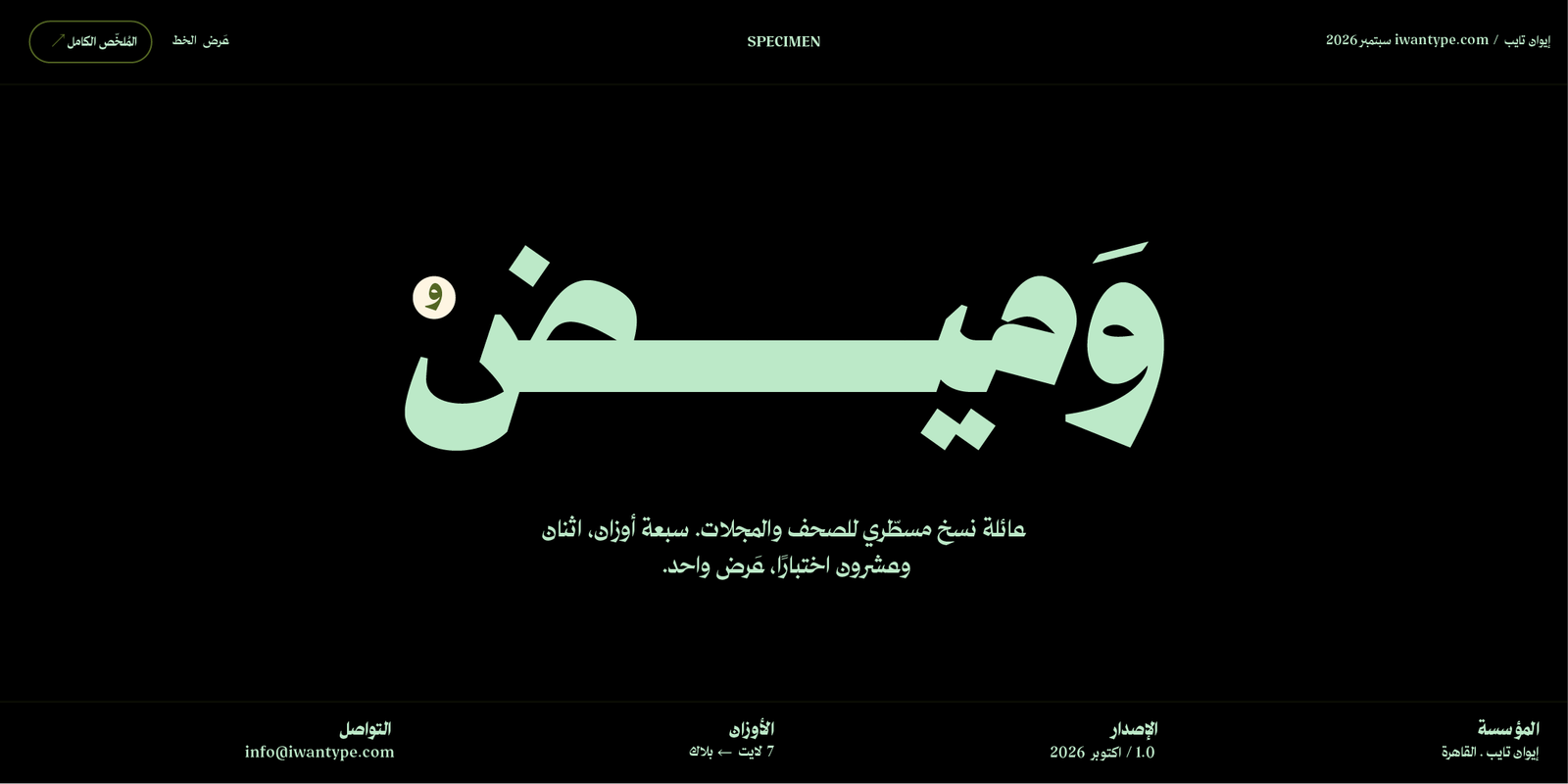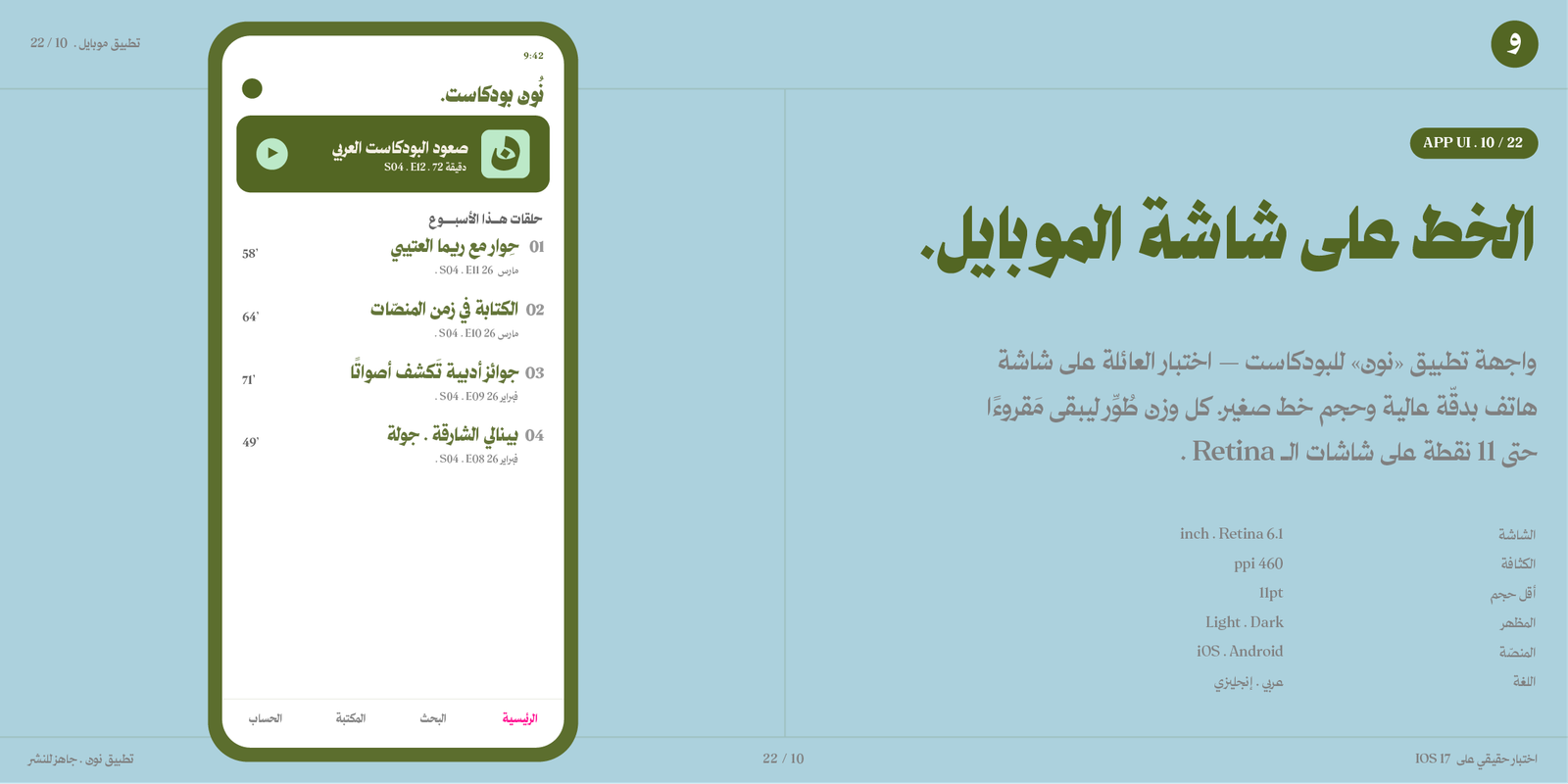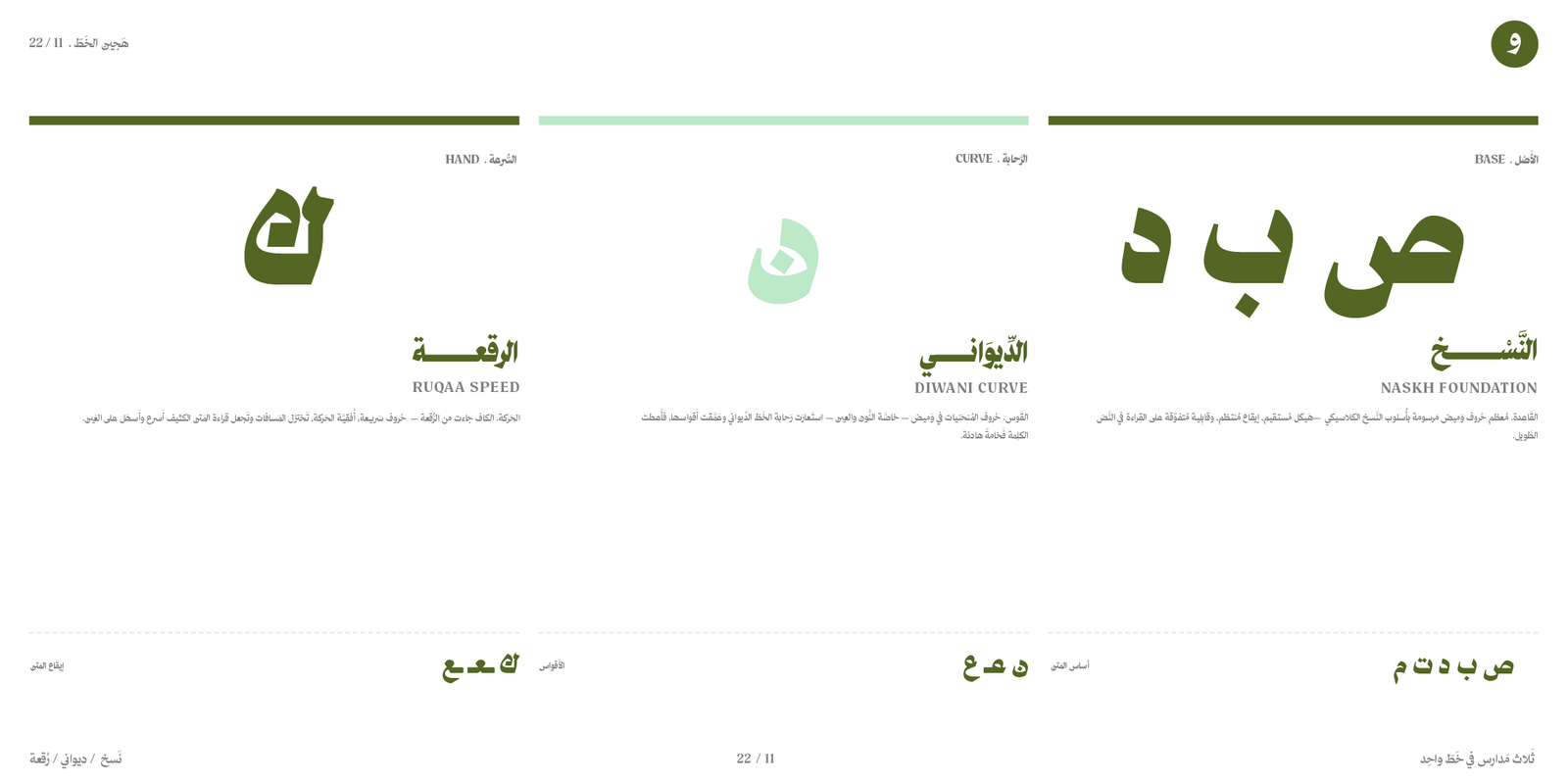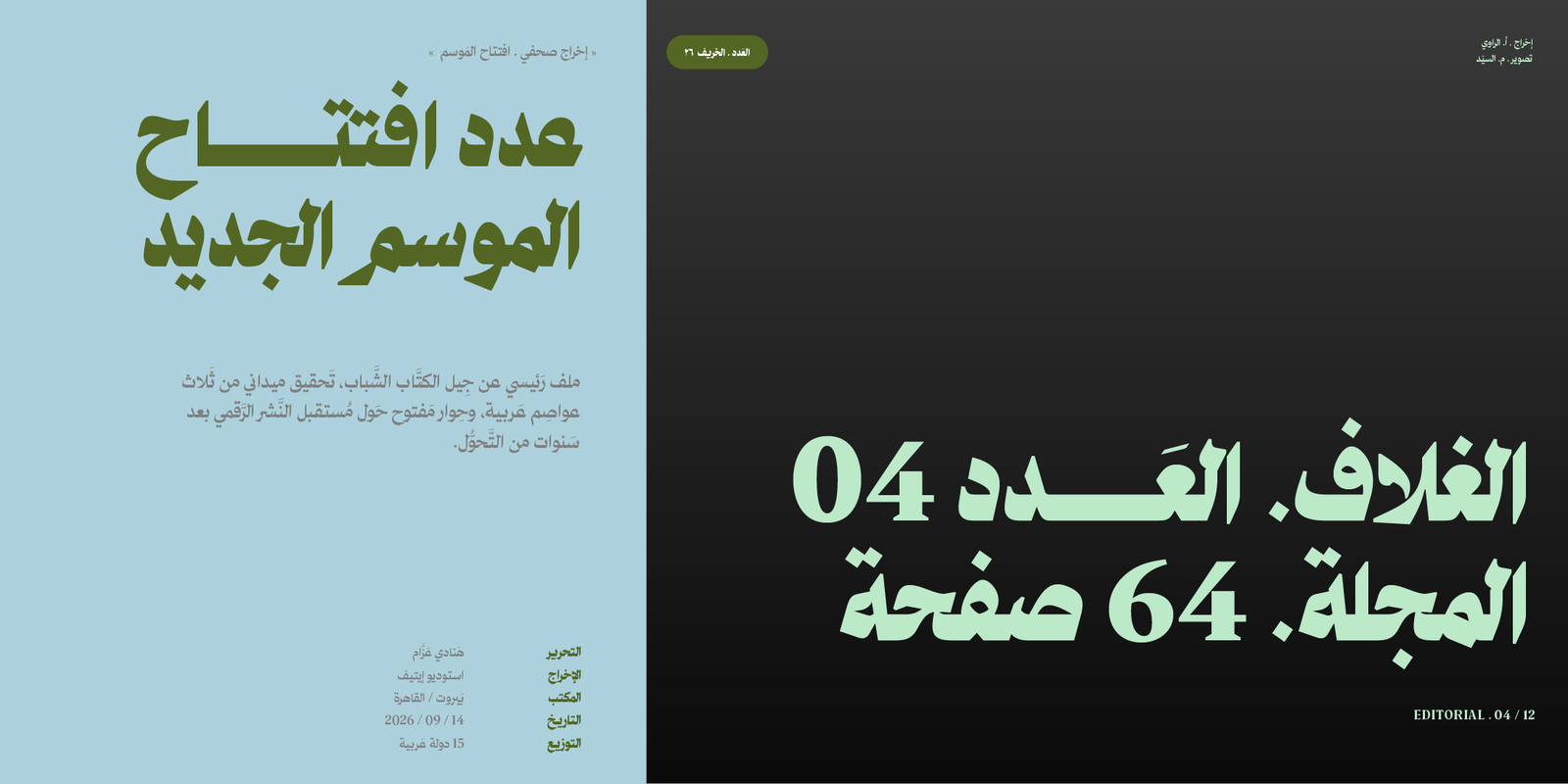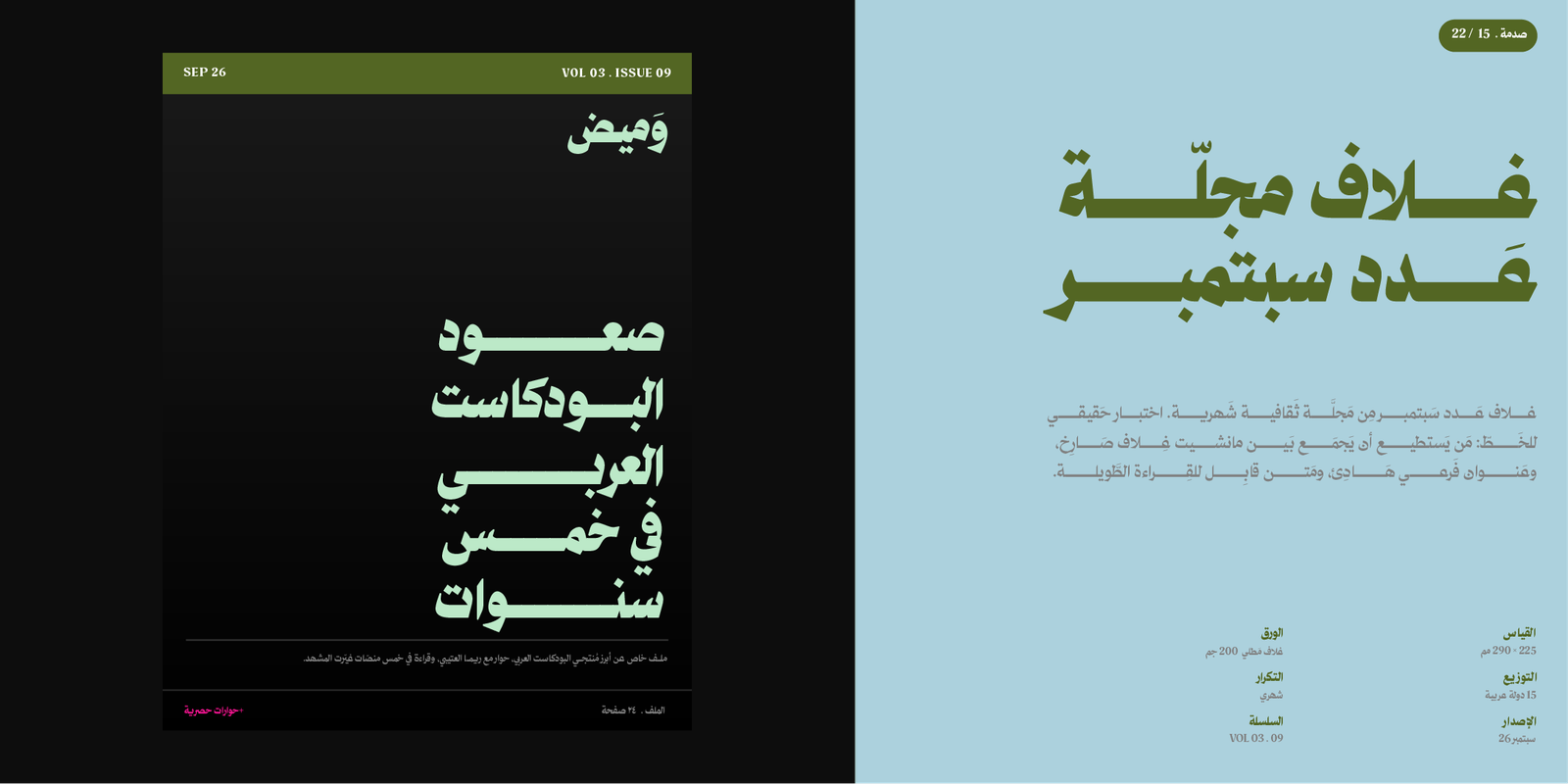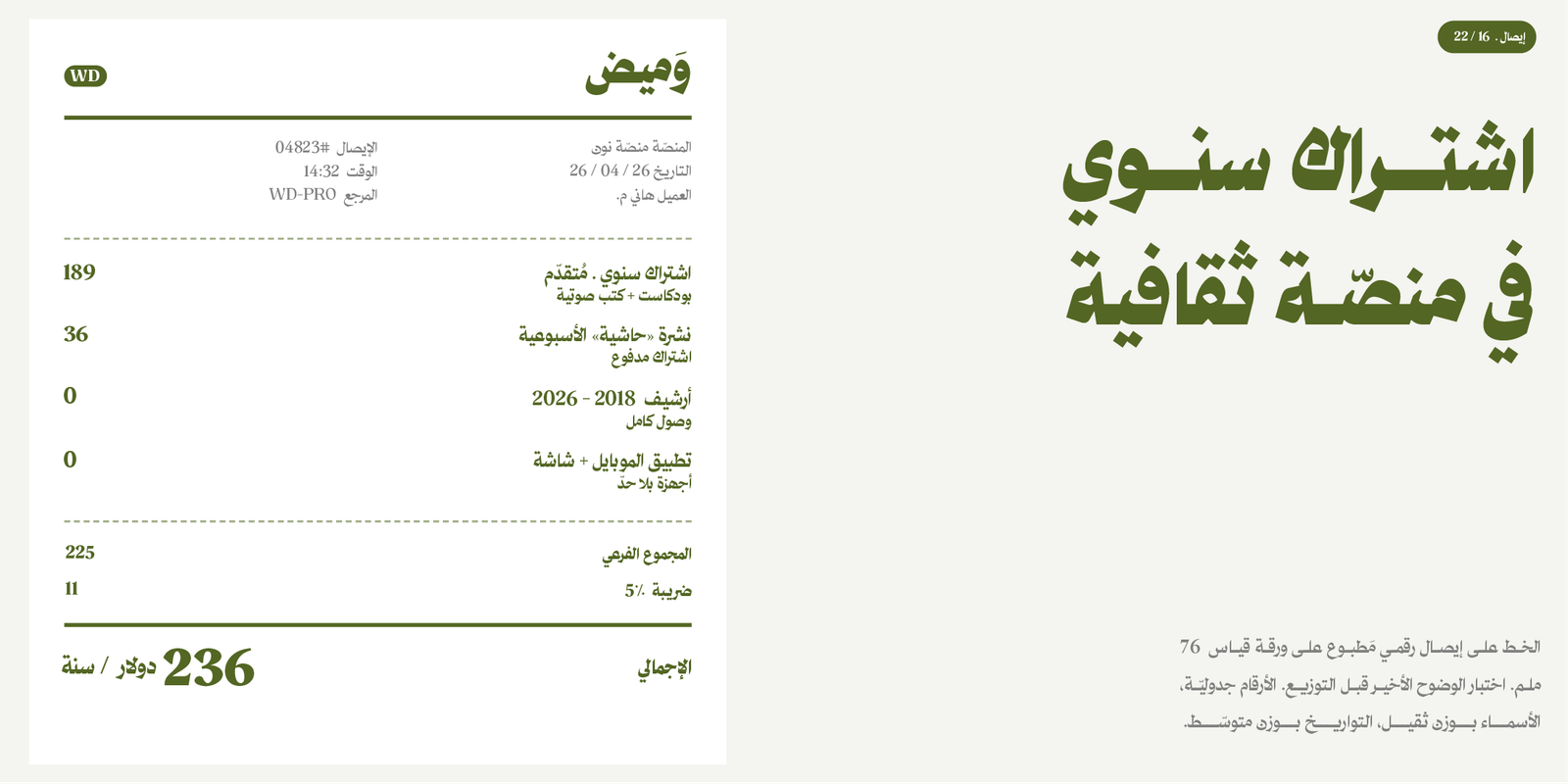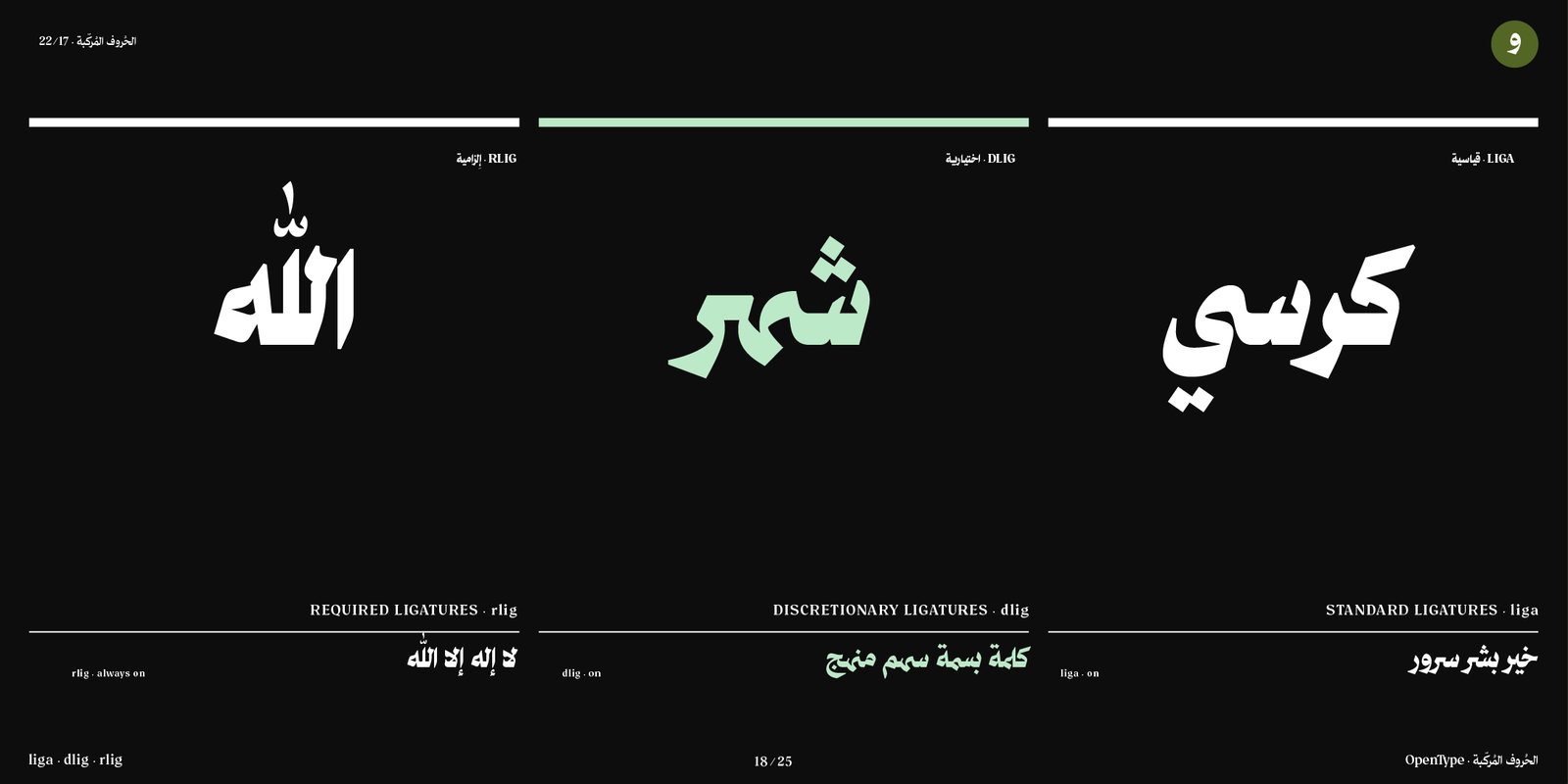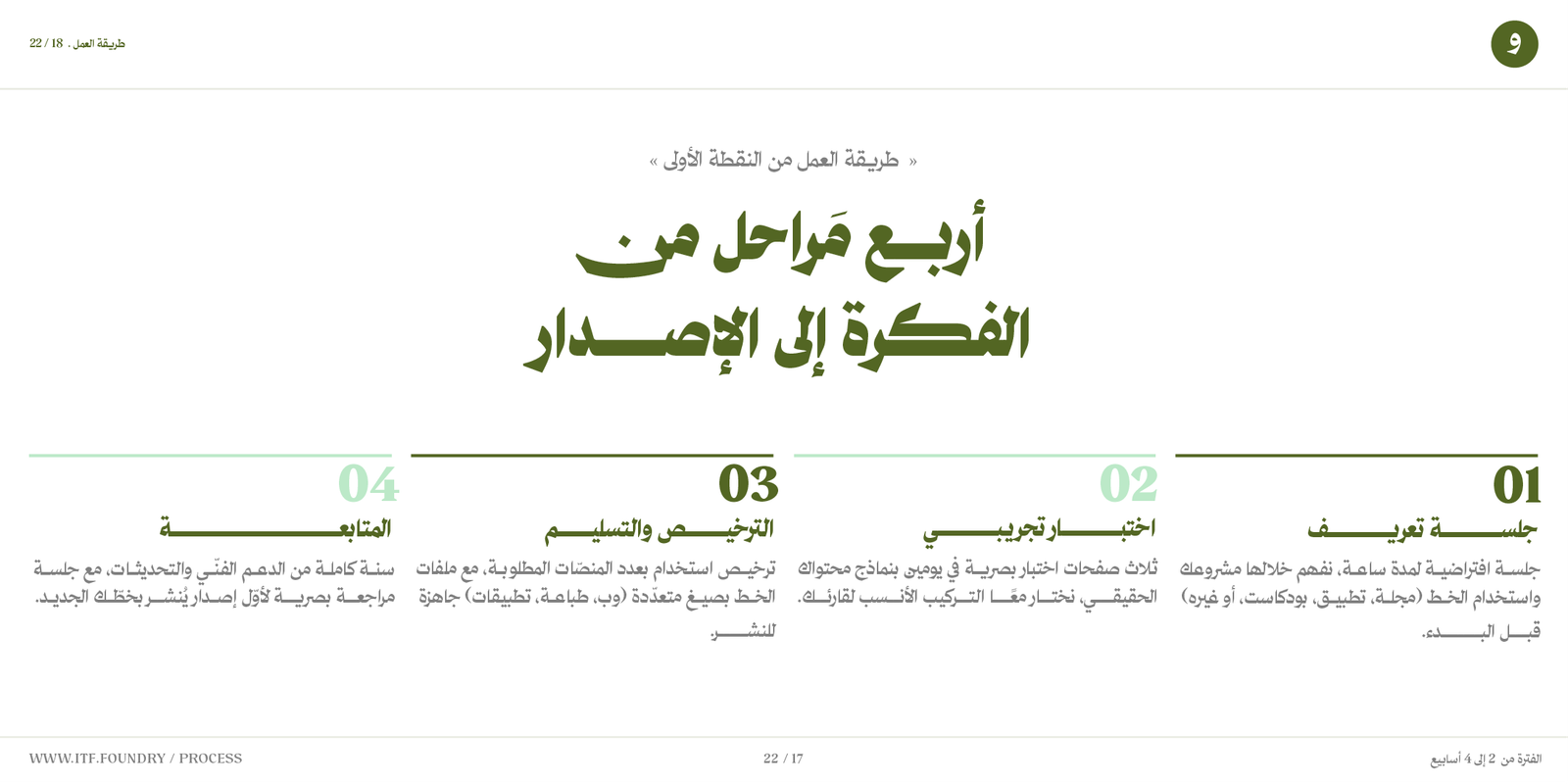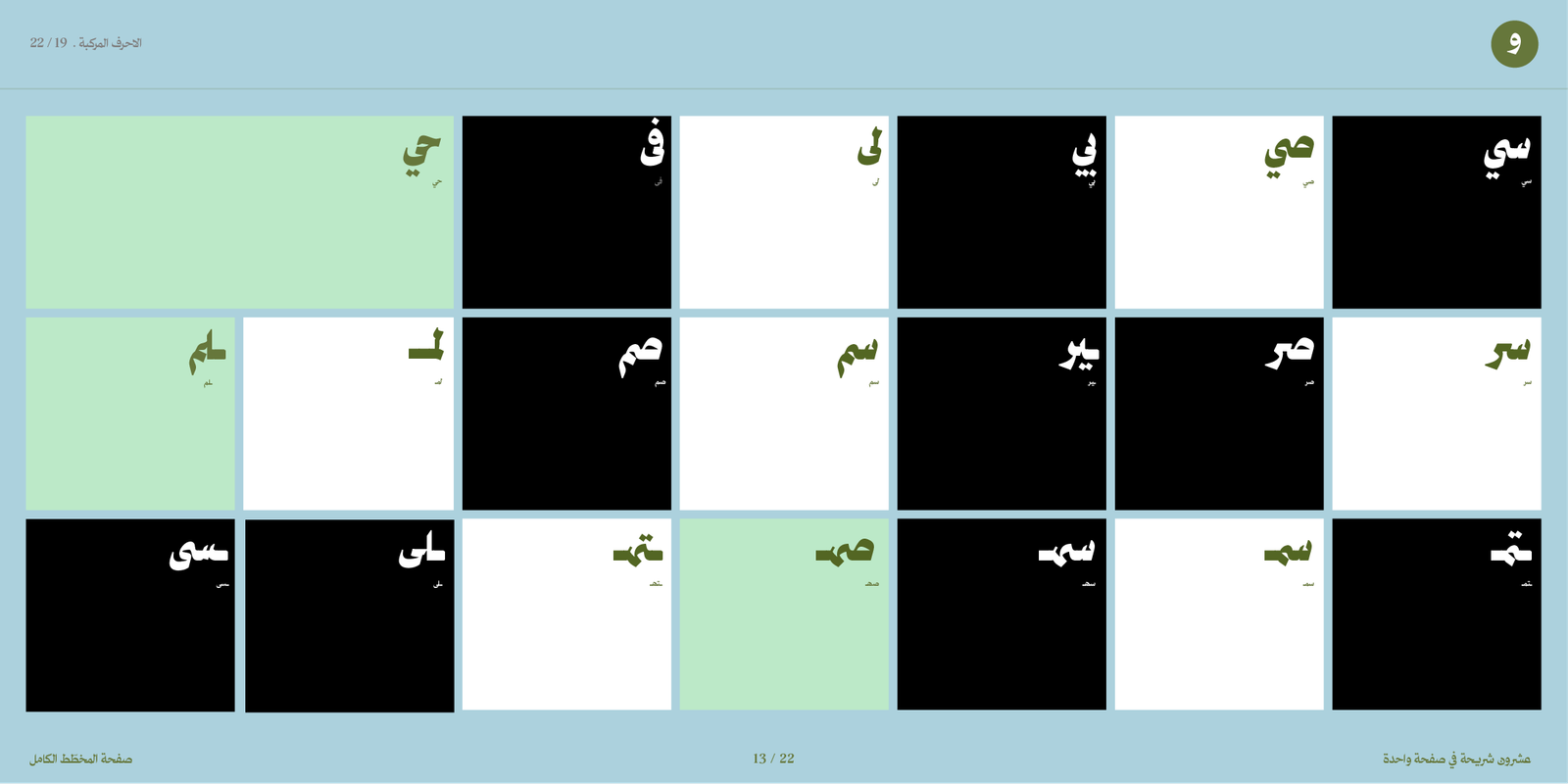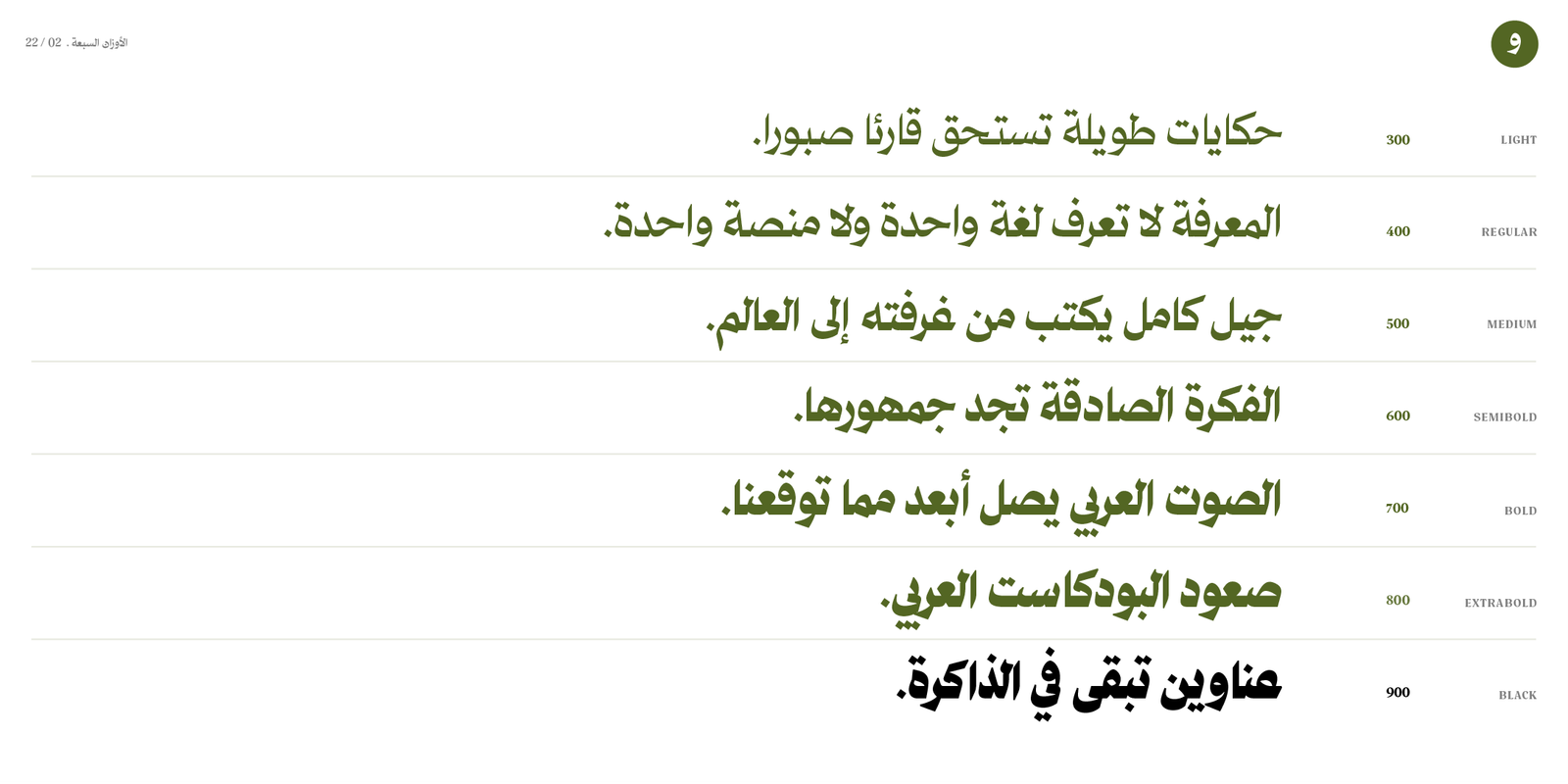
خط وميض – Wameed typeface – خط نسخ حديث للصحف والمجلات
خط «وميض» خط نسخ عربي حديث بُني على أساس النسخ المسطّري: هيكل مستقيم، وإيقاع منتظم، وحروف مرسومة للعناوين والعناوين الفرعية والنص المتوسط.
يجمع «وميض» في قلم واحد بين ثلاثة أنواع من الخطوط العربية: النسخ والديواني والرقعة.
تضم العائلة سبعة أوزان من الخفيف إلى الأسود، إلى جانب نسخة متغيرة بمحور وزن متصل من 300 إلى 900، تتيح ضبط ثقل السطر بدقة بين العنوان والمتن من ملف واحد.
يناسب «وميض» العناوين والعناوين الفرعية والنص المتوسط، على الورق وعلى الشاشة، حيث يحتاج المشروع إلى خط نسخ يحفظ للعنوان حضوره ويبقى مقروءاً حين يصغر.
مميزات خط وميض:
يتضمن الخط العديد من مزايا OpenType التي تضفي عليه مرونة وتنوعًا في الاستخدام، مثل:
- أحرف مرسلة (تُفعَّل بإضافة “ءء” بعد الحرف)
- تأتي مع كل خيار نسخة «وميض مرسلة» في ملف منفصل بأوزان الخيار نفسه، تظهر فيها الأحرف المرسلة مباشرة دون تفعيل خصائص OpenType.
- أحرف مركّبة تُحسّن سلاسة التراكيب وتناسق النص.
- يدعم رمز الريال السعودي والريال العُماني ،ويتم تفعيلهما تلقائيًا عند كتابة الاختصارات: ر.س للريال السعودي ر.ع للريال العُماني
الأوزان: 7 أوزان